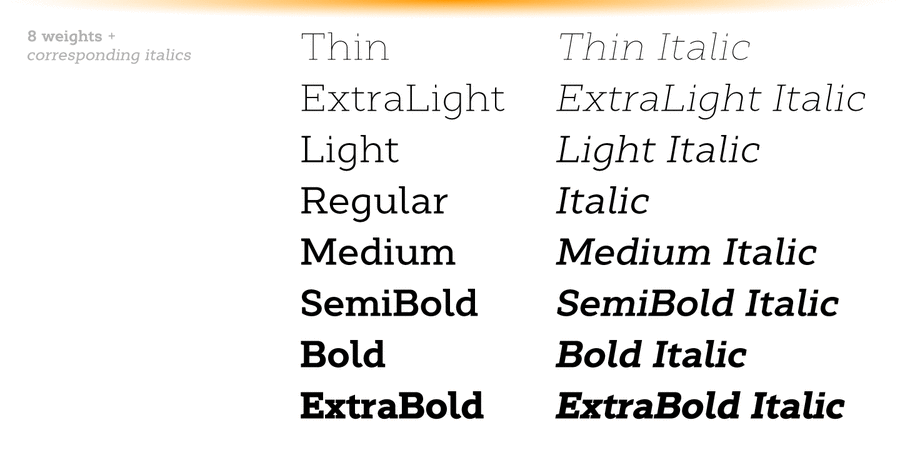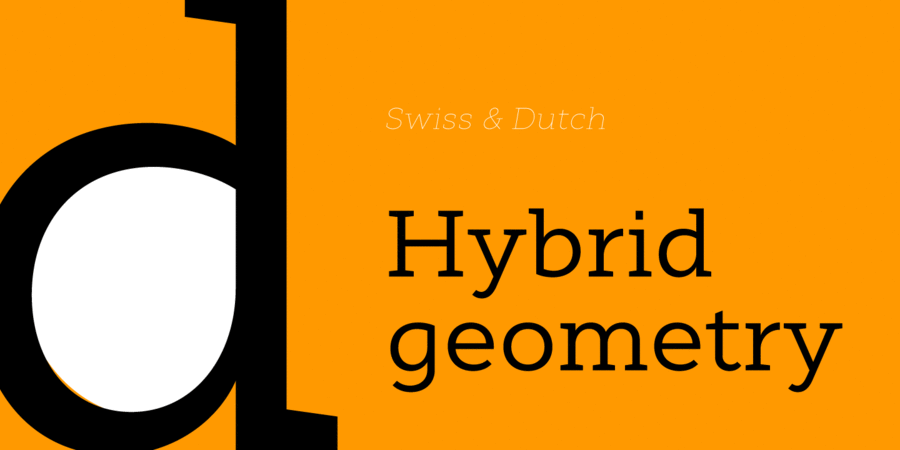
Cyntho Next Slab – брусковий компаньйон шрифту Cyntho Next. Це сучасний геометричний брусковий шрифт, в основі якого гібридна краплеподібна контрформа. Має широкий спектор підтримки мов, включаючи кирилицю. Шрифт має численні OpenType-фічи. Він ідеально підходить для журналів, плакатів, реклами, фірмового стилю і багато чого іншого.
Шрифт розробив Андрій Константинов у 2019 році.
Асоціації з сімейством шрифтів Cyntho Next SlabОсобистість і характер гарнітури:
точний, легкий, холодний, модний, діловий, стійкий, стабільний, статичний, рівний, різкий, чіткий, дротяний, худий, твердий, серйозний, гострий, креслярський, інженерний, переконливий, Простий, прямокутний, залізний, сталевий, надійний, впевнений, індустріальний, техногенний, міський, урбаністичний, відповідальний, формальний, спокійний, гармонійний, універсальний, зрозумілий, нейтральний, середній, звичайний, врівноважений, космополітичний, ненав'язливий, помірний, технічний, сучасний, логічний, непомітний, практичний, оптимальний, доступний, культурний, освічений, якісний, розумний, суворий, мотивуючий, сильний, авторитетний, значний, військовий, армійський, гучний, амбітний, мужній, робочий
архітектура, дизайн, конструктор, техніка, прилад, наука, технології, креслення, інженер, Місто, офіс, бухгалтер, промисловість, верстат, інструмент, математика, хімія, урбаністика, фінанси, медицина, годинник, ліки, освіта, суспільство, юрист, адвокат, правосуддя, економіка, бізнес, банкнота, монета, банк, фізика, вчитель, суд, влада, політика, гроші, новини, аптека, механіка, машинобудування, армія, ремонт, охорона, захист, страйкбол, поліція, будівництво, взуття, цегла, вантажівка, далекобійник, сталевар, робочий Гарнітура має ознаки стилів:
— Гарнітура асоціюється з віком: